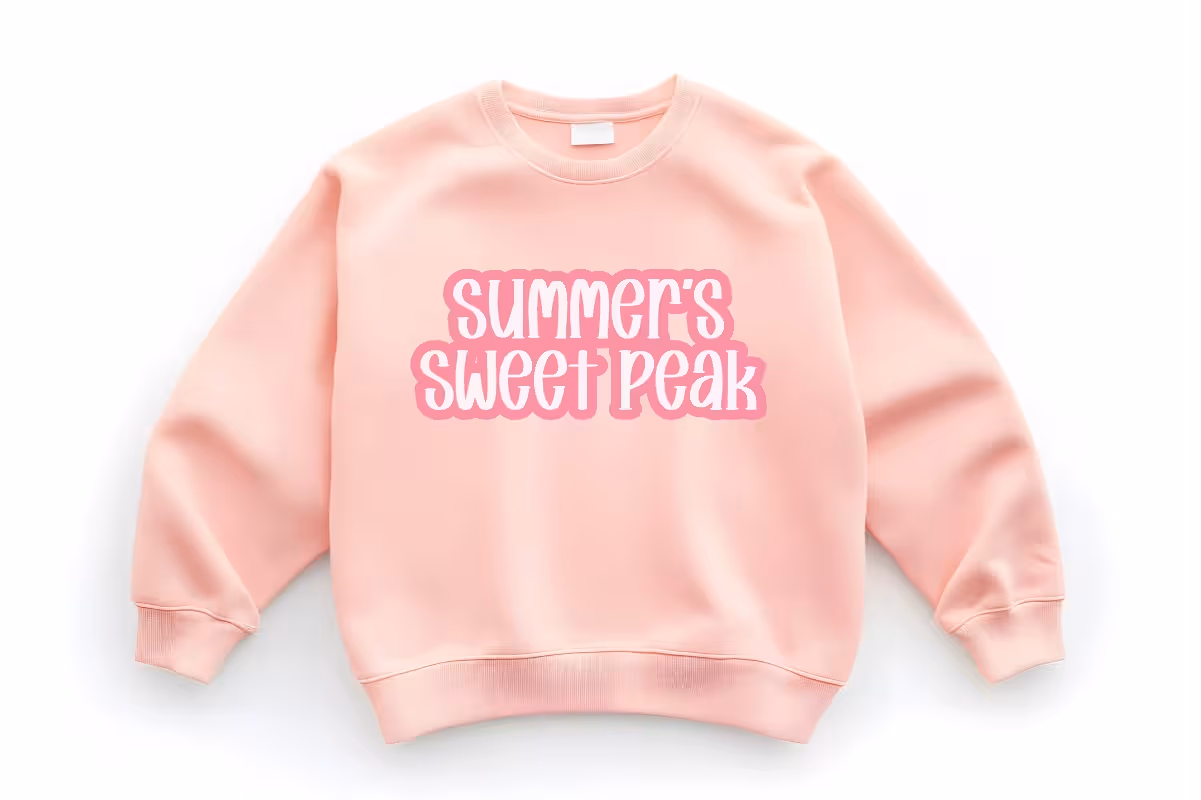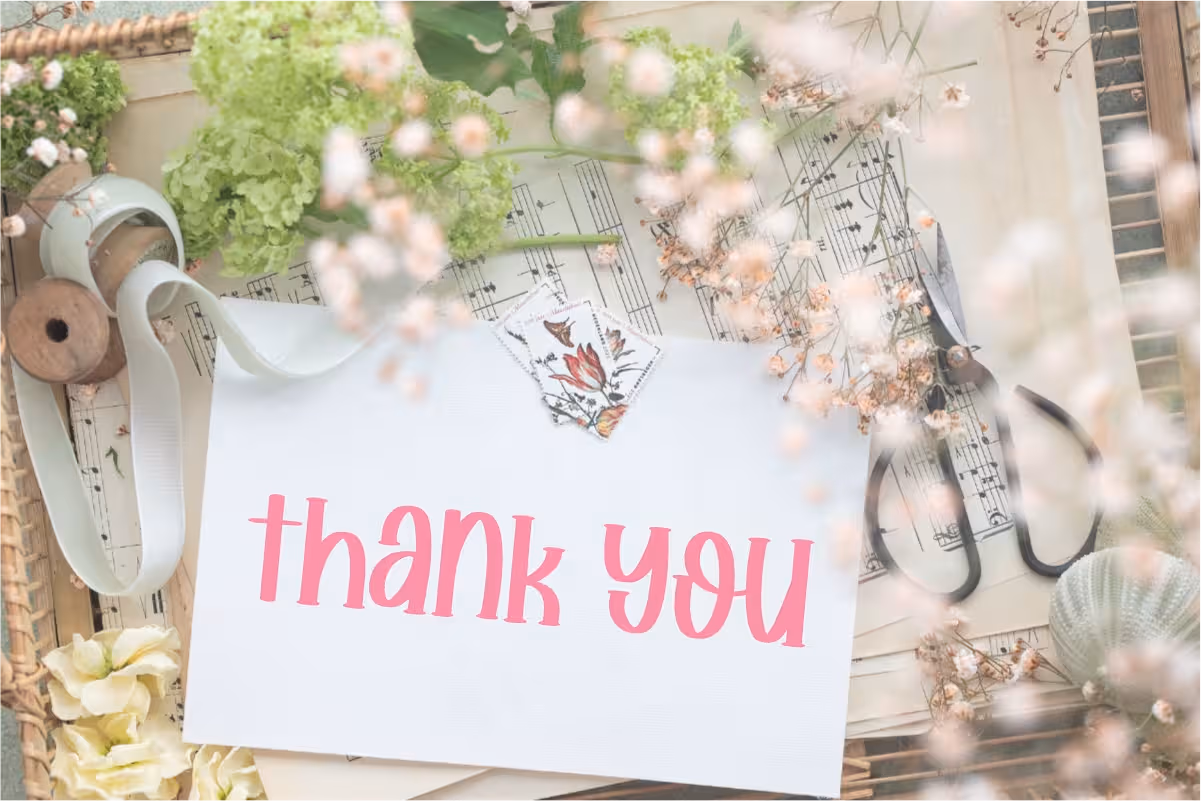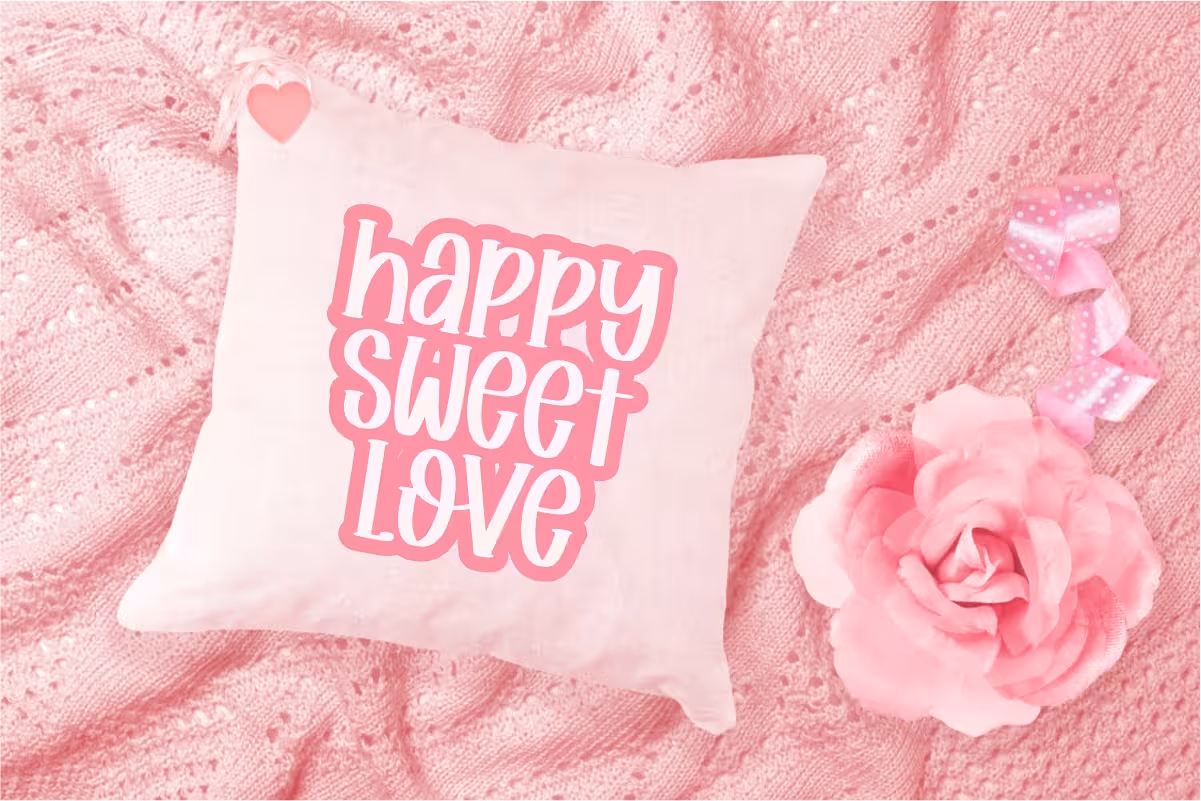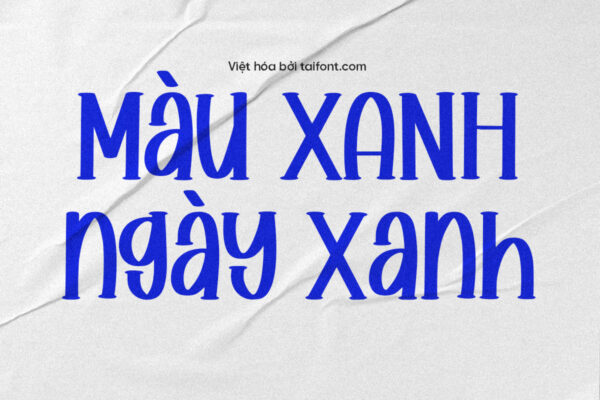
Giới thiệu về Font TF Sweet August Việt hóa
TF Sweet August Việt hóa là một font chữ trang trí nổi bật với vẻ đẹp mềm mại, duyên dáng và đầy lãng mạn, gợi cảm giác về những ngày hè ngọt ngào và những khoảnh khắc đáng yêu. Font này toát lên phong thái nhẹ nhàng, tinh tế và một chút bay bổng, lý tưởng để tạo điểm nhấn độc đáo và thu hút mọi ánh nhìn trong các thiết kế đòi hỏi sự ấm áp và cảm xúc.
Với sự duyên dáng trong từng đường nét, tính thẩm mỹ cao và phong thái dễ chịu, Sweet August là lựa chọn hoàn hảo cho các thiết kế muốn truyền tải sự ngọt ngào, lãng mạn và sự gần gũi:
- Thiết kế cốc/ly: Hoàn hảo để in các câu nói, lời chúc, hoặc họa tiết chữ lên cốc, ly sứ, hoặc các vật phẩm lưu niệm. Nét chữ mềm mại, lãng mạn của font sẽ làm cho chiếc cốc trở nên cá tính, ấm áp và là món quà ý nghĩa, đặc biệt cho các dịp kỷ niệm hoặc quà tặng cá nhân.
- In áo thun: Lý tưởng để in các câu trích dẫn, slogan, hoặc họa tiết chữ lên áo phông, áo hoodie. Font này sẽ giúp áo thun trở nên nổi bật, phong cách và truyền tải thông điệp một cách dễ thương, lãng mạn.
- Thiết kế gối: Phù hợp để in các thông điệp yêu thương, tên riêng, hoặc các họa tiết chữ lên gối ôm, gối tựa. Nét chữ mềm mại của font sẽ làm cho chiếc gối trở nên ấm cúng và là món quà ý nghĩa cho người thân yêu.
- Thiết kế thiệp và quà tặng: Rất phù hợp cho thiệp chúc mừng, thiệp sinh nhật, hoặc các nhãn dán quà tặng, giúp tạo không khí lãng mạn và đáng yêu.
Với TF Sweet August Việt hóa, bạn có thể dễ dàng thổi hồn lãng mạn, sự tinh tế và vẻ đẹp ngọt ngào vào các thiết kế, tạo ra những sản phẩm không chỉ đẹp mắt mà còn đầy cảm xúc và sức hút, đặc biệt hiệu quả cho các dự án cần sự mềm mại và thân thiện.